カンタンでちょっぴり深いロゴづくり 掛け合わせてつくる、やさしい一歩
インプレスグループでデザイン分野のメディア事業を手がけるエムディエヌコーポレーションは、甲谷一氏著書による、ロゴづくりに必要なノウハウをぎゅっと詰め込んだ一冊『カンタンでちょっぴり深いロゴづくり 掛け合わせてつくる、やさしい一歩』を発売した。
『カンタンでちょっぴり深いロゴづくり 掛け合わせてつくる、やさしい一歩』では、ロゴづくりをやさしく解説するために、「掛け合わせる」という考え方をベースに説明。
「形×文字、形×形」という視覚的な面はもちろんのこと、さらに一歩進めた「形×コンセプト」という意味も含んでおり、たくさんのテクニックを駆使しなくても十分にデザインができる。
シンプルゆえに奥が深いロゴづくりですが、初心者の方にもわかりやすく、つくり方のヒント・アイデアに悩んでいる方にも役立つ内容が盛り込まれている。
また、クライアントの要望やコンセプトをもとに、どのように考えながら文字や形を選び、ロゴをつくっているのか実際の過程を詳しく紹介。
ロゴづくりに必要なノウハウをぎゅっと詰め込んでいる。
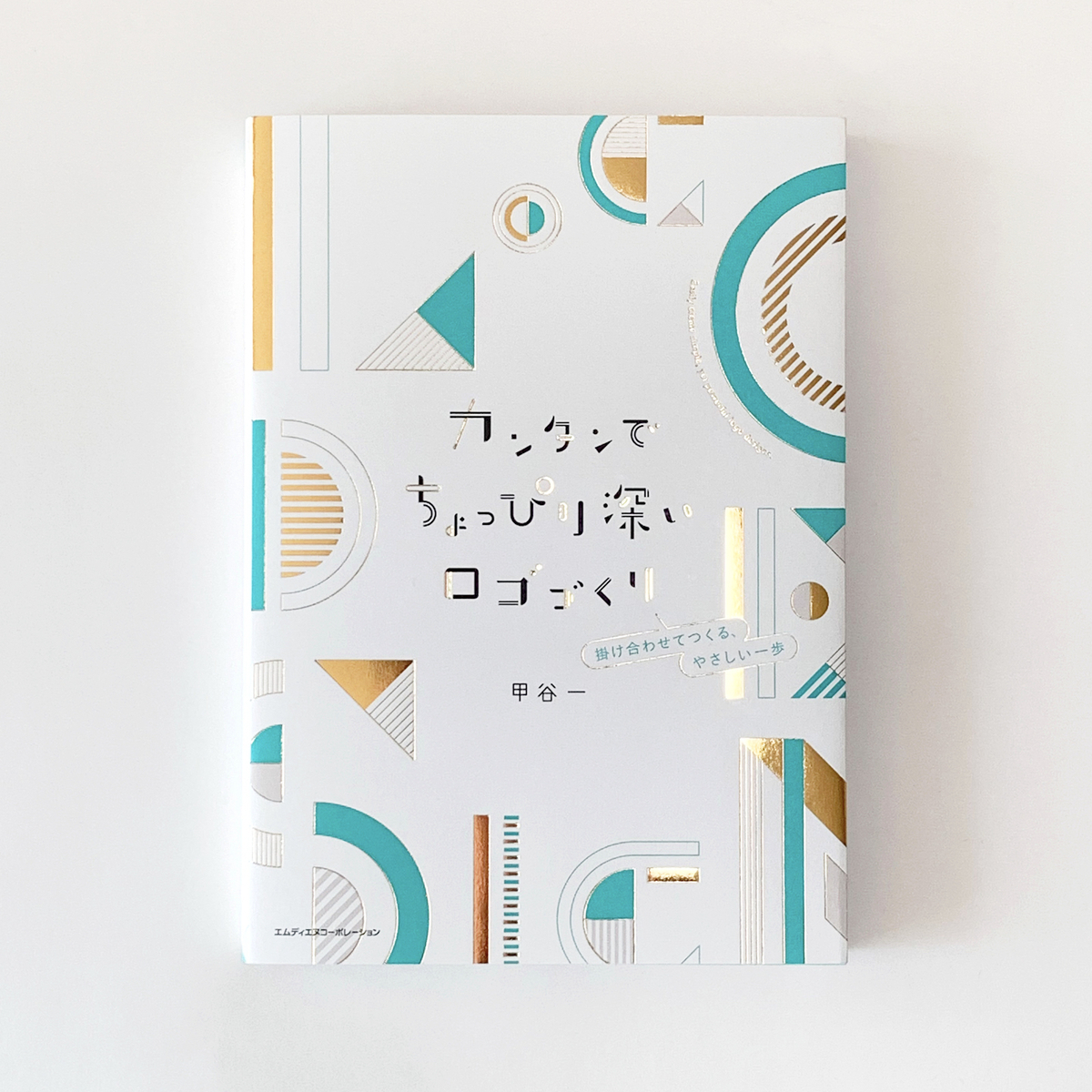
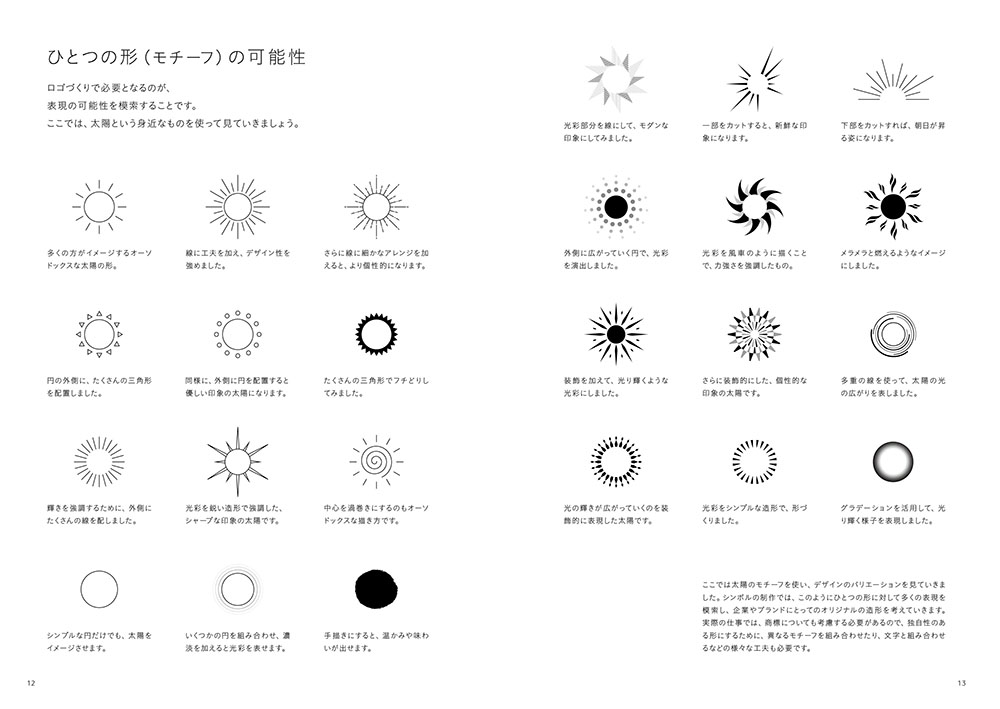
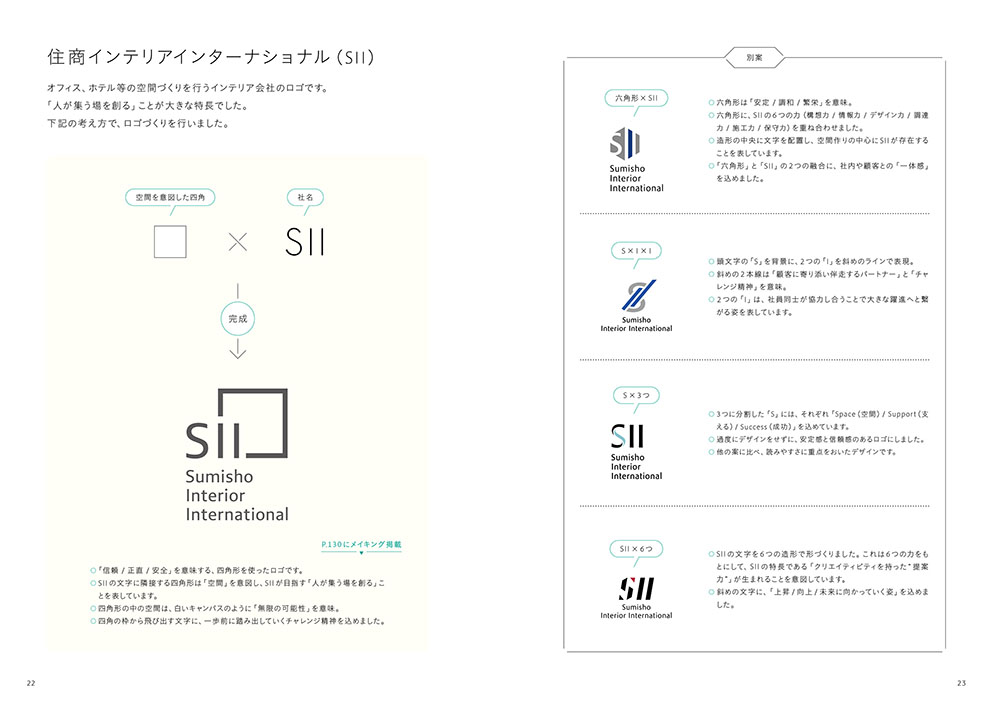
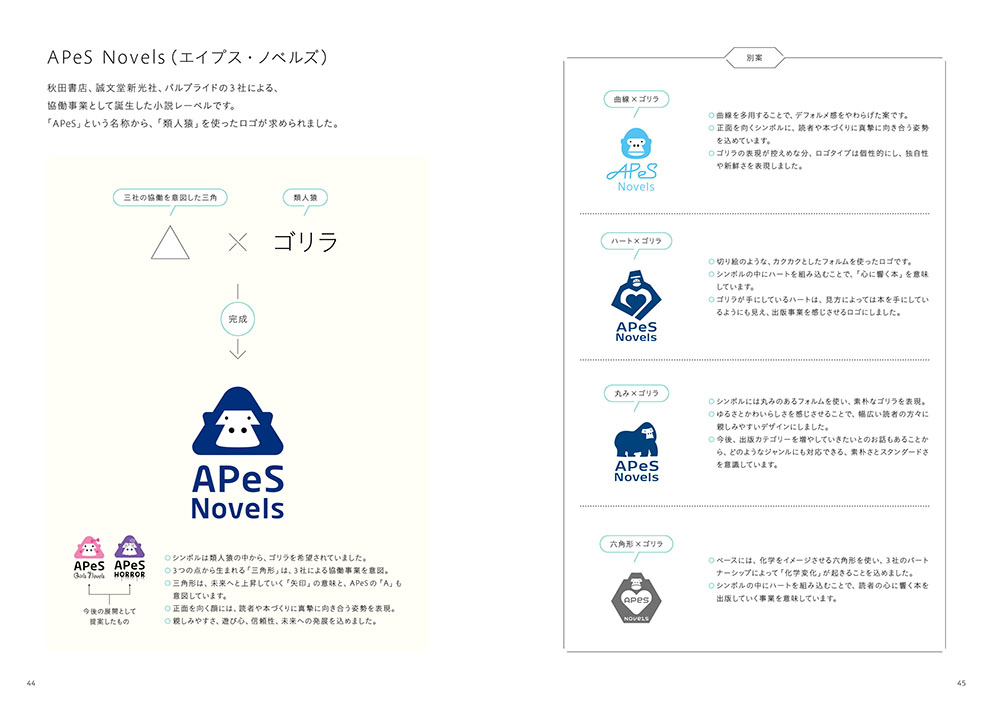
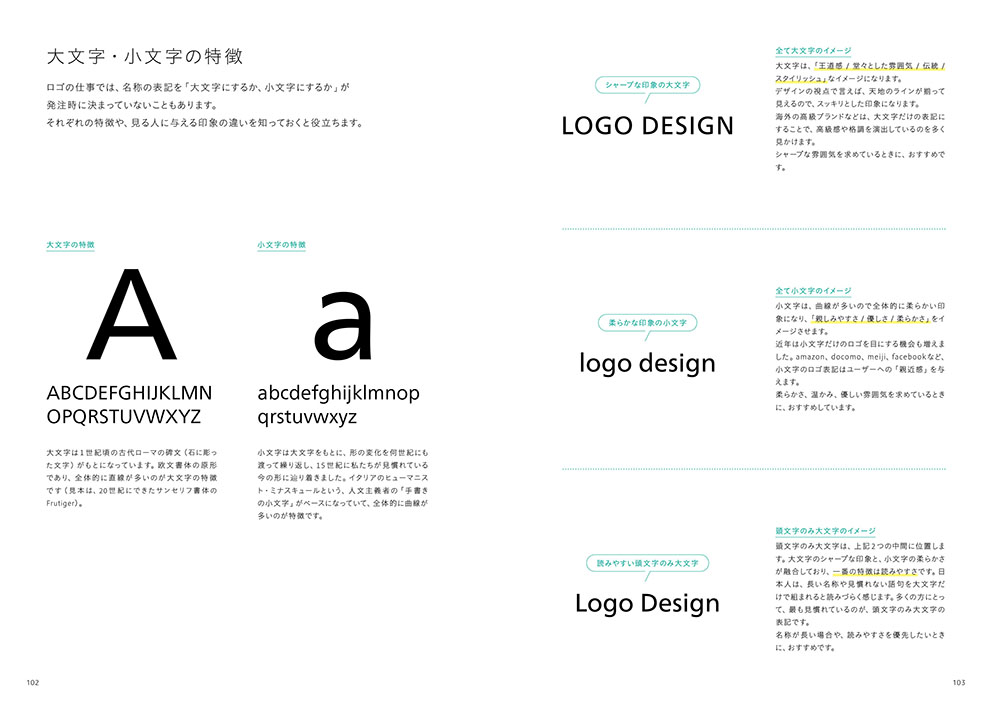
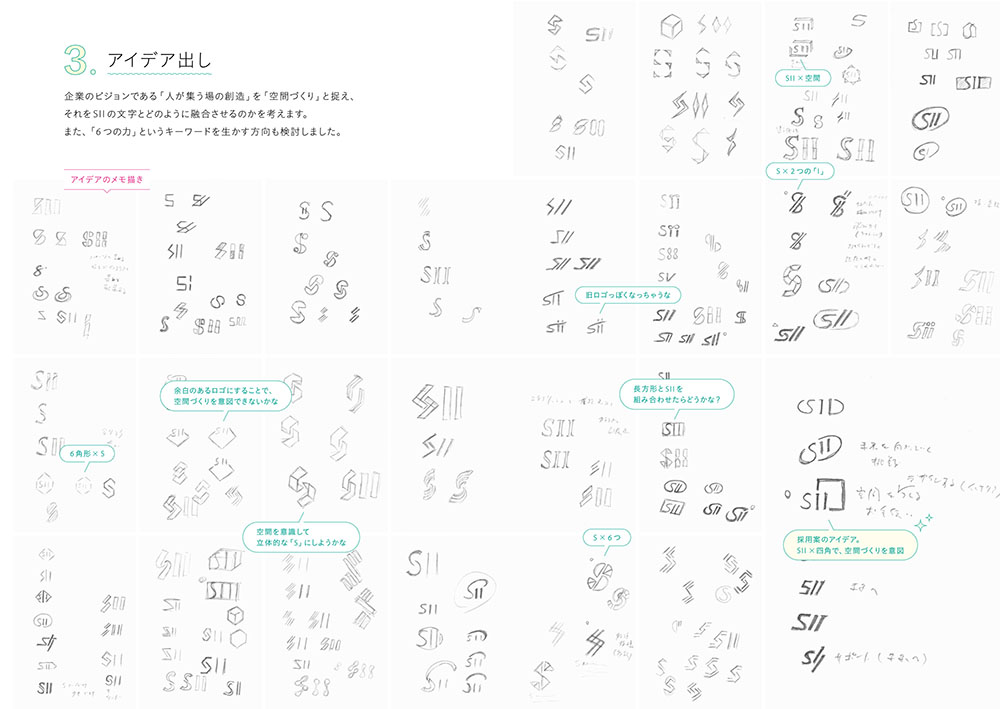
甲谷一Profile●アートディレクター、グラフィックデザイナー。2006年(有)Happy and Happy 設立。ロゴデザインをはじめ、タイポグラフィを効果的に使ったデザインを得意とする。近年は企業のロゴ開発やコーポレートツールなどを多数手がける。主な仕事に「RESONAC」「ジャパネット」「UBE三菱セメント」「住商インテリアインターナショナル」「ENEXIA」「WEMEX」等のコーポレートロゴ、「NHK BSプレミアム / BS1」チャンネルロゴ(2011~2020)、建築家・安藤忠雄氏の美術館「ANDO MUSEUM」ロゴ、「デザインノート / イラストノート」雑誌タイトルロゴ等。オンライン講座に「甲谷一のデザイン逆再生」(schoo)、「ロゴデザインディレクション基礎講座」(宣伝会議)等。ニューヨークTDC 賞の他、東京ADC、東京TDC、JAGDA、日本タイポグラフィ年鑑入選。著書『ロゴDAYS 甲谷一のデザインと思考』(誠文堂新光社)、『たのしいロゴづくり』(ビー・エヌ・エヌ)、『きれいな欧文書体とデザイン』(ビー・エヌ・エヌ)等多数。
『カンタンでちょっぴり深いロゴづくり 掛け合わせてつくる、やさしい一歩』の内容
形と文字と、掛け合わせの基本
実例で見る、掛け合わせるロゴ
メイキングでわかる、ロゴづくりの現場 1
現場で役立つ、ロゴのノウハウ
[コラム]私のロゴを支えるもの
メイキングでわかる、ロゴづくりの現場 2
[Q&A]6つの素朴なギモン
ロゴと文字の基礎